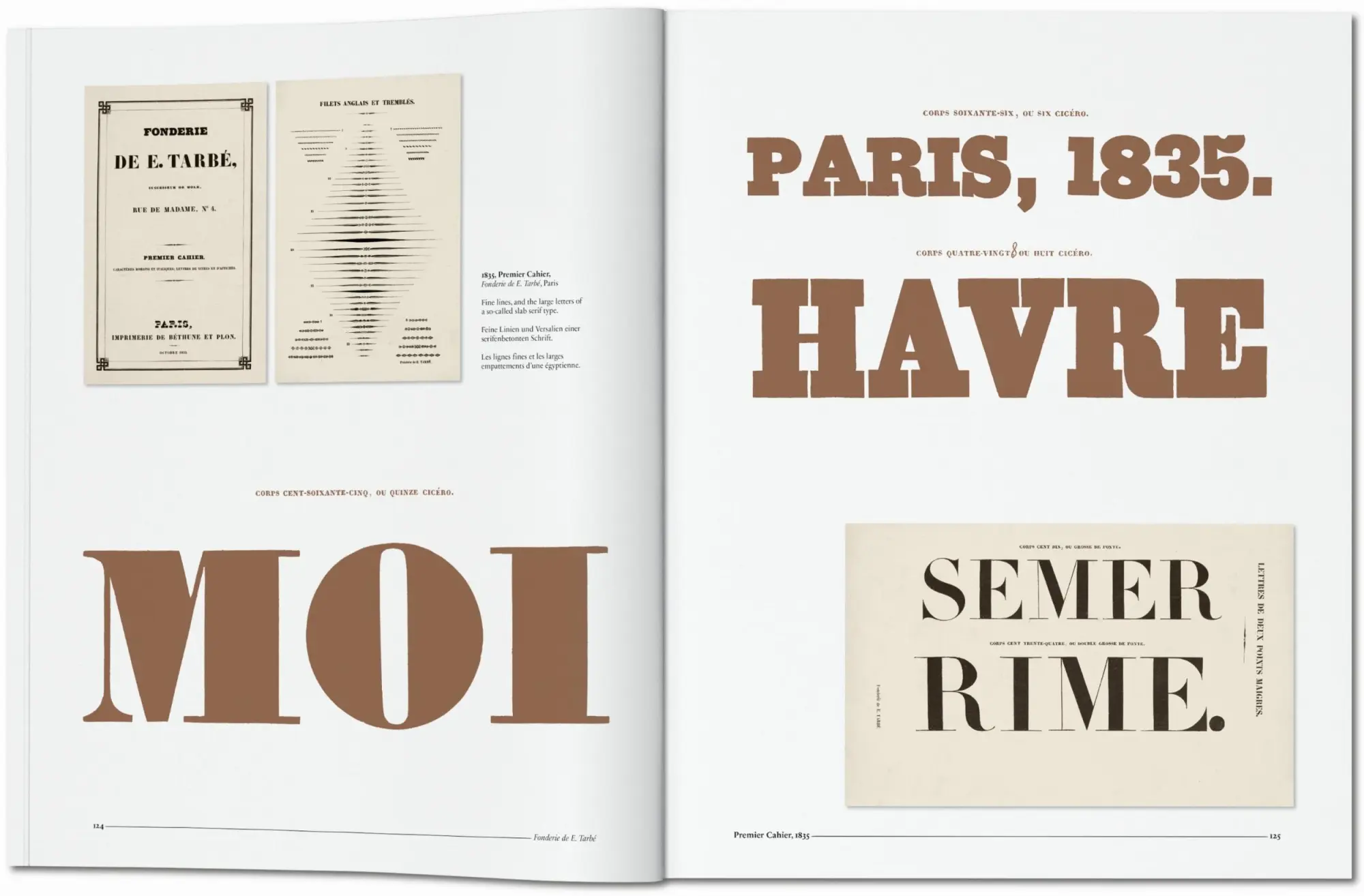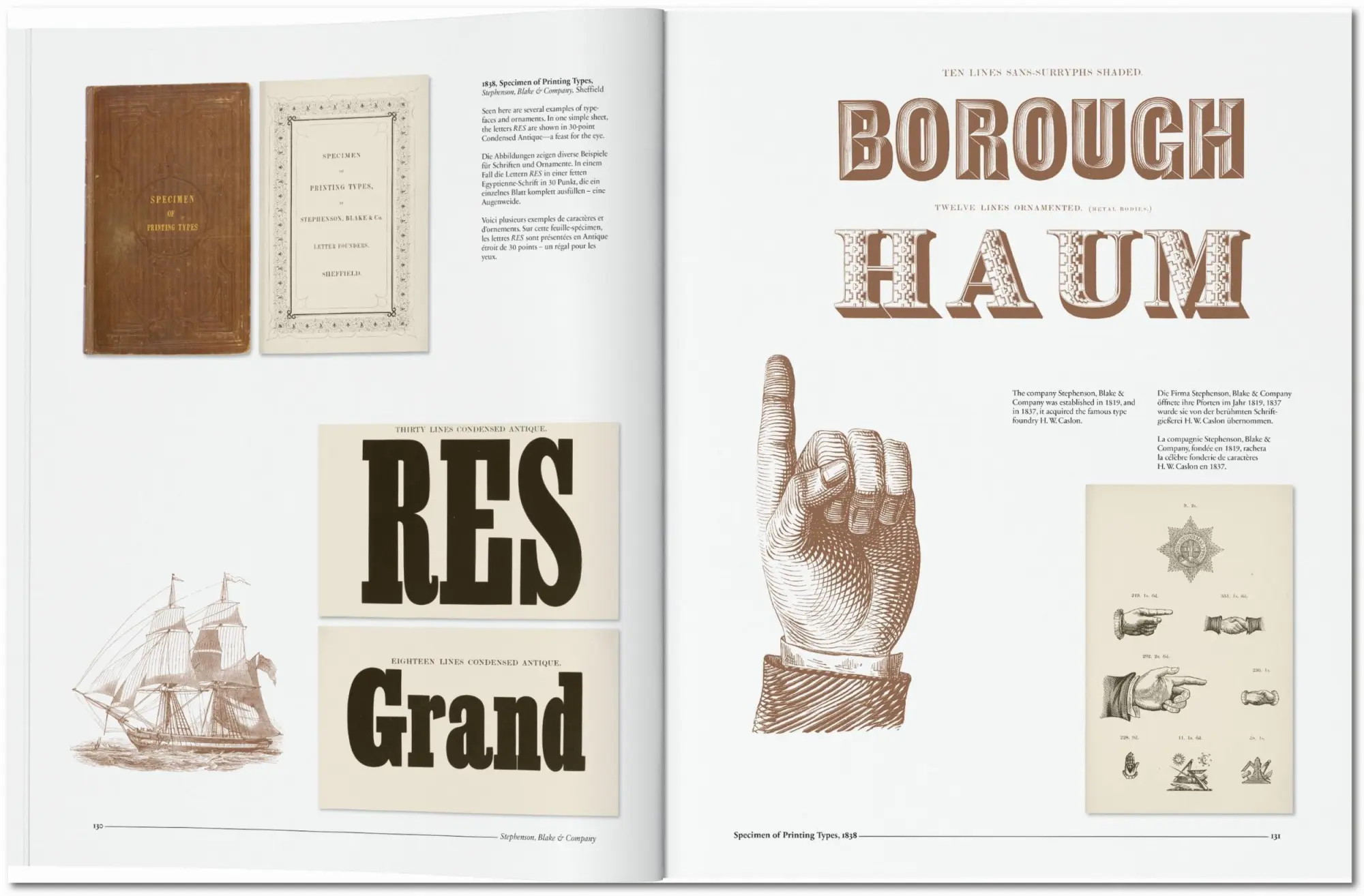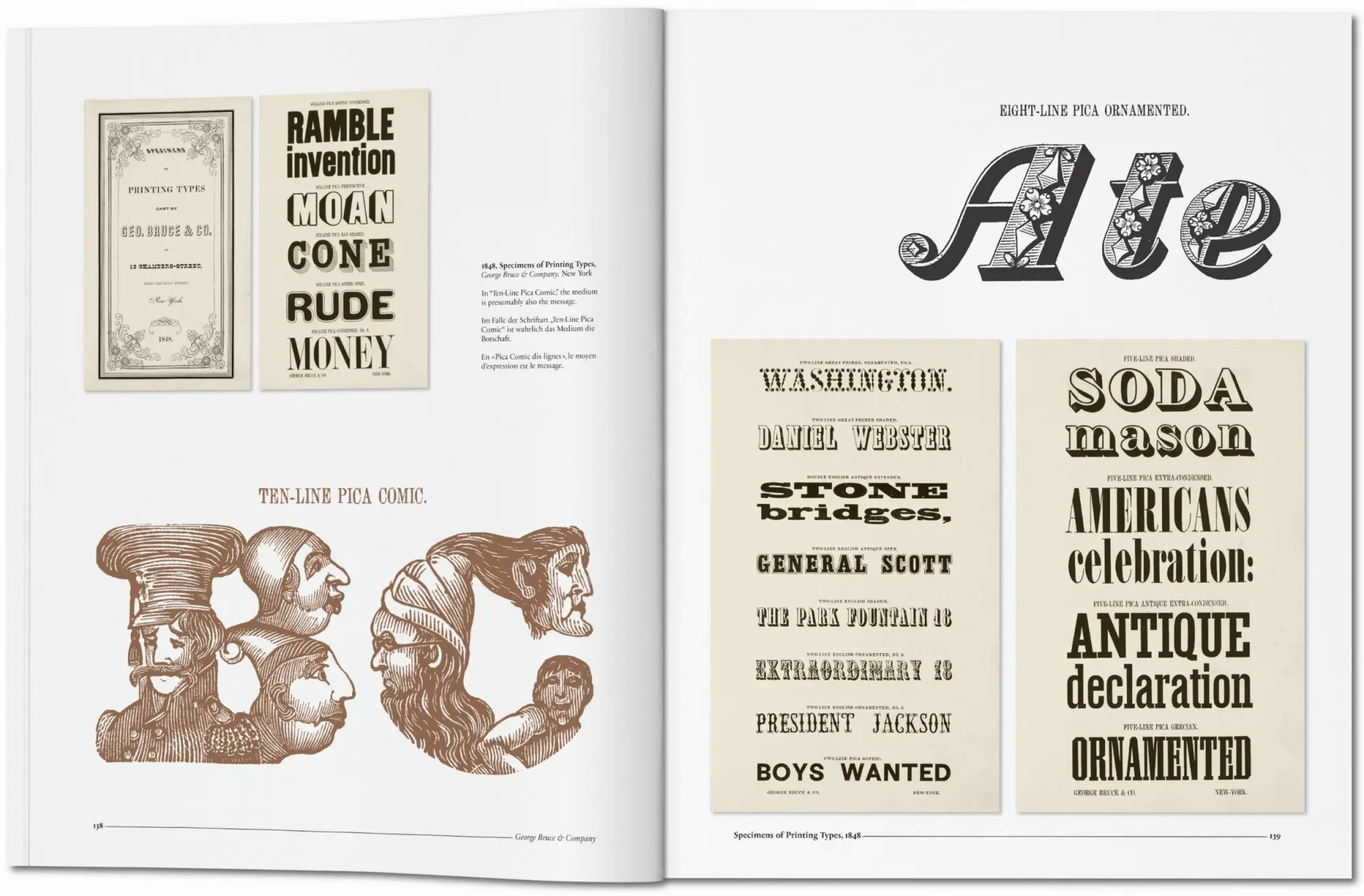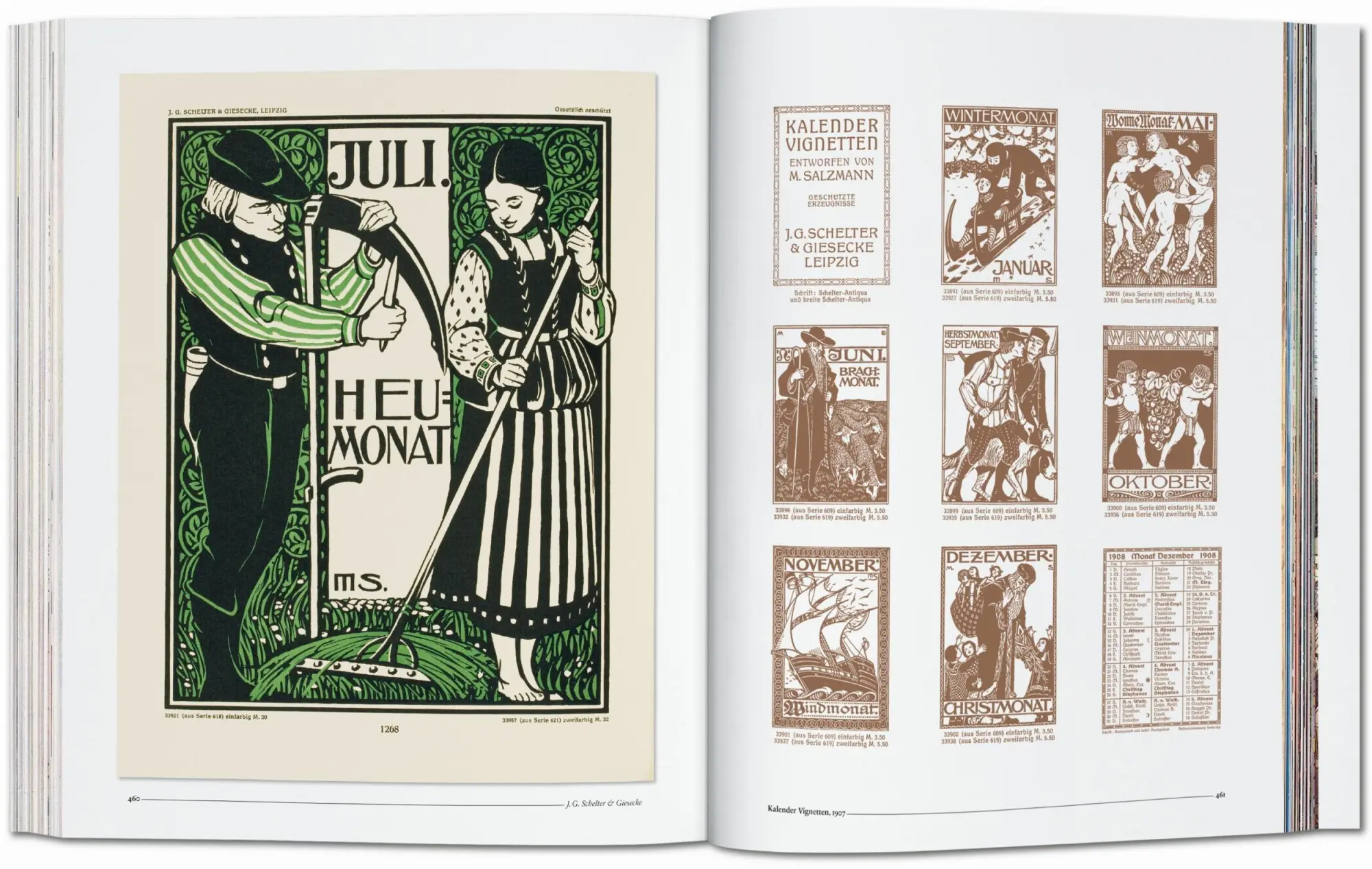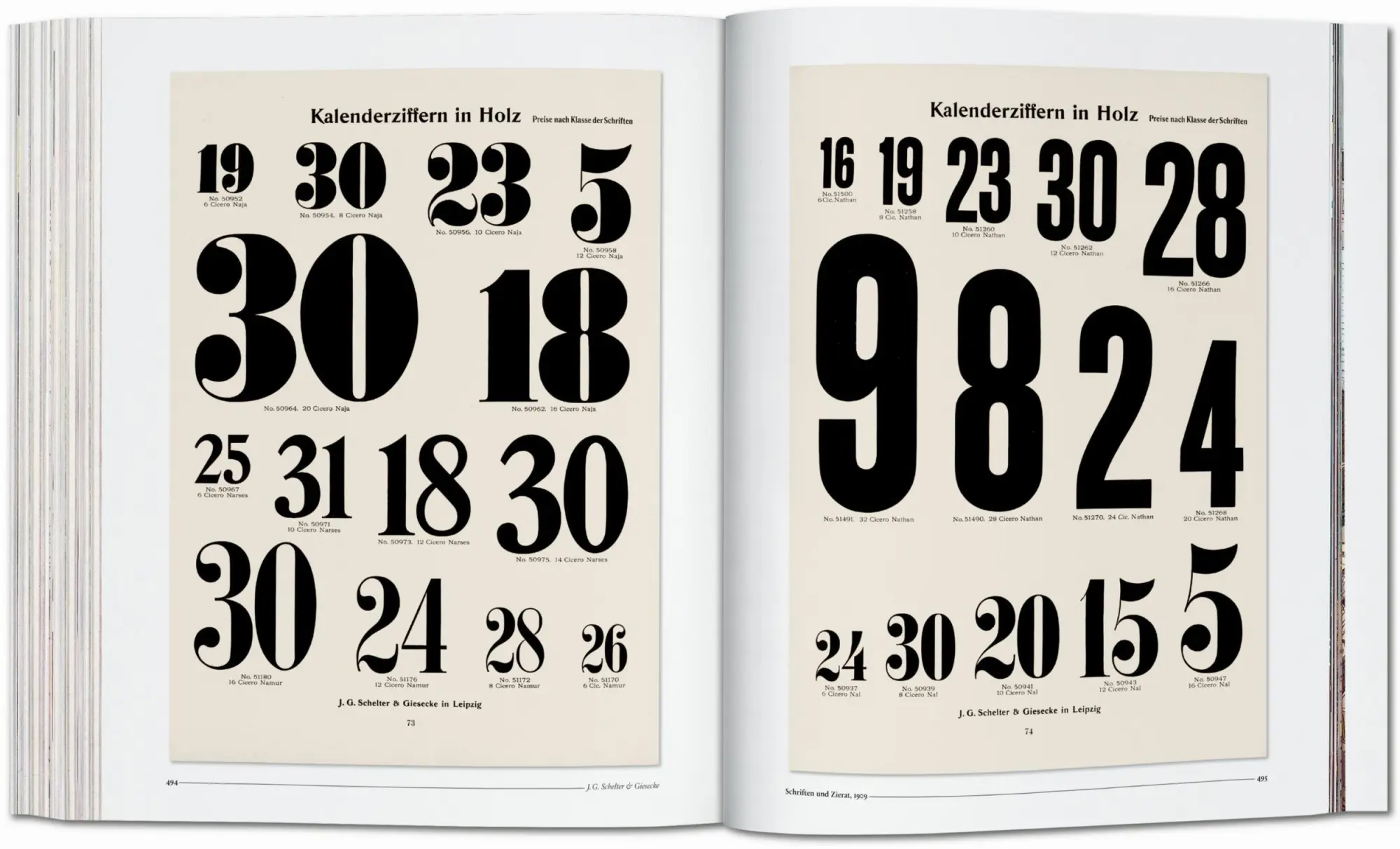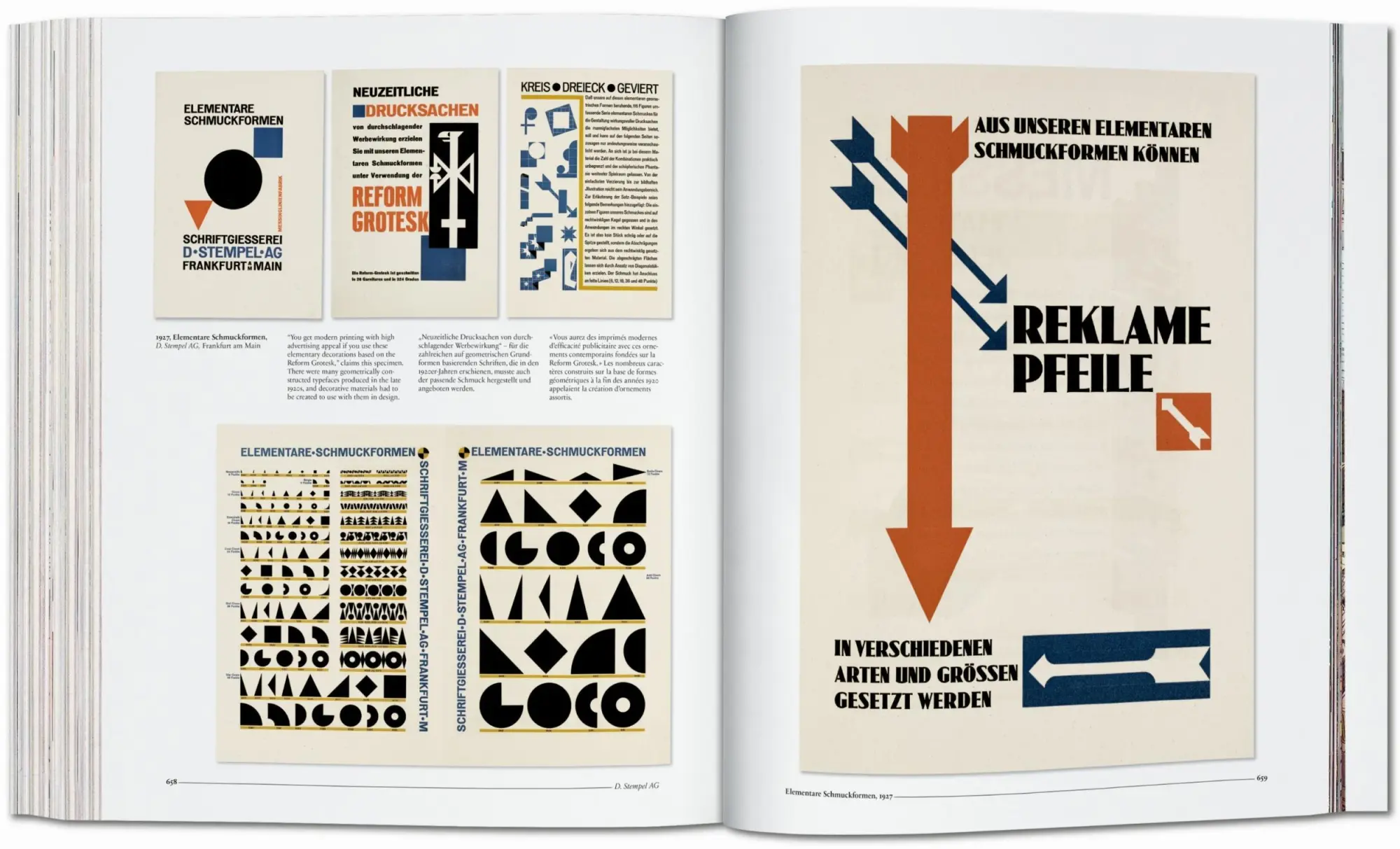
Das hätt' ich gerne schriftlich: die elegantesten Schriftarten der Druckgeschichte in historischen Schriftmusterbüchern. Diese auf einer angesehenen niederländischen Sammlung basierende, umfangreiche Ausgabe zeichnet die Entwicklung der Druckbuchstaben anhand von ausnehmend schönen Katalogen nach. Sie zeigt Typenproben in mageren, kursiven, fetten, halbfetten, schmalen und breiten Fonts. Bordüren, Ornamente, Initialen und Verzierungen sowie exemplarische Lithografien, Briefe von Schildermalern, Inschriftenschnitzern und Kalligrafien sind ebenso enthalten.
Der erste Teil stellt Schrifttypen aus der Zeit vor dem 20. Jahrhundert vor und enthält Essays des Herausgebers Cees de Jong und des Sammlers Jan Tholenaar. Der zweite Teil deckt die Phase von 1900 bis zur Mitte des 20. Jahrhunderts ab und enthält einen geschichtlichen Abriss von Alston W. Purvis. Mit Werken von Schriftendesignern wie William Caslon, Fritz Helmuth Ehmcke, Peter Behrens, Rudolf Koch, Eric Gill, Jan van Krimpen, Paul Renner, Jan Tschichold, A. M. Cassandre, Aldo Novarese und Adrian Frutiger.